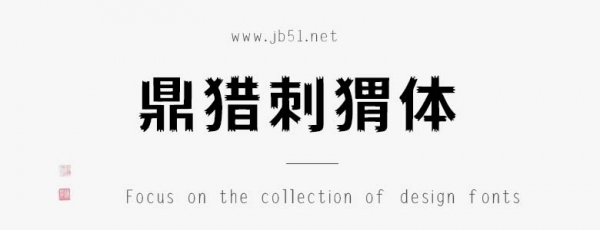
鼎獵刺猬體由鼎獵字庫出品的藝術字體,以黑體為藍本衍化的創(chuàng)意字體,整體有撕裂的鋸齒狀邊緣,有穩(wěn)健和善良的內在,卻有著棱角和鋒芒,像是刺猬,有鋒芒而不失柔軟的善良和堅強的意志,具有很好的視覺感,適合應用于藝術設計、平面宣傳設計、網頁設計,書法字帖等領域。有需要的朋友快來本站下載使用吧。
鼎獵刺猬體,是一款以黑體為藍本衍化的創(chuàng)意字體,整體有撕裂的鋸齒狀邊緣,有穩(wěn)健和善良的內在,卻有著棱角和鋒芒,像是刺猬,有鋒芒而不失柔軟的善良和堅強的意志。很像仍在火熱上映《哪吒2》的魔丸哪吒。鼎獵刺猬體適合美食餐飲、展會展覽、企業(yè)文化,以及報刊封面、餐飲茶飲、美妝護膚等各個行業(yè)。踏入2025年,鼎獵將持續(xù)推出更多字體。
考慮到字體應盡可能滿足各類型的姓和名,鼎獵刺猬體以簡體中文漢字編碼國家標準(GB2312編碼)為標準,共計設計了多達7415個字符,其中漢字6769個??梢詽M足絕大部分印刷設計等要求。